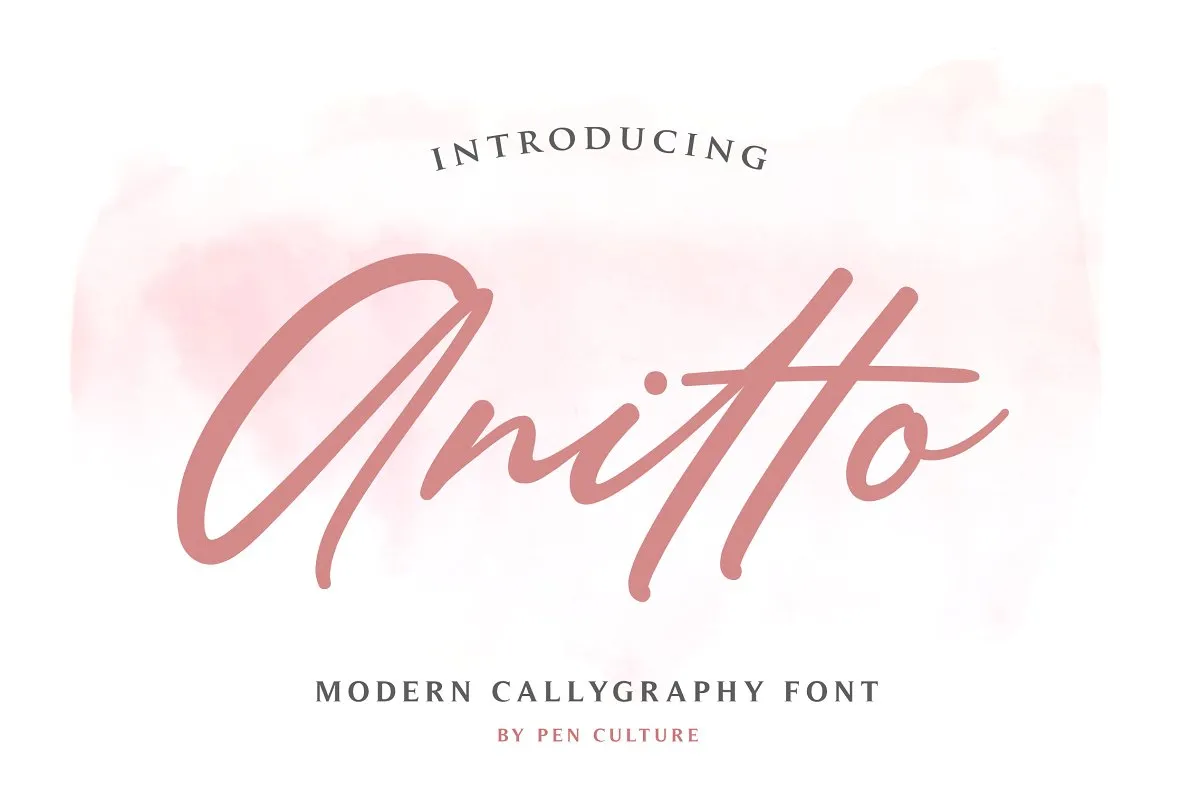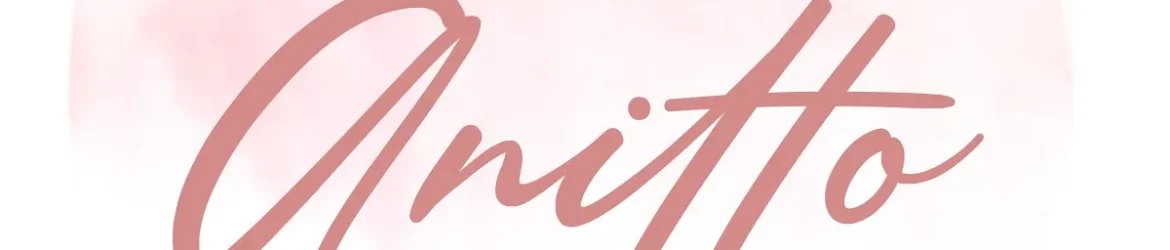
Anitto Calligraphy Font – Download Grátis
A Anitto Calligraphy Font é uma nova opção para designers que buscam expressar texturas delicadas e curvas suaves. Inspirada no encanto das manhãs dominicais nas pequenas vila do Brasil, esta fonte apresenta linhas leves e perfeitas para diversos usos. Com seu design cuidadoso por Pen Culture, a Anitto Calligraphy Font é ideal tanto para aplicativos em grandes tamanhos quanto para uso em mídias digitais menores. Sua natureza fluida e delicada tornam-a uma opção perfeita para criar texturas e estilos script elegantes em qualquer projeto. Combinar esta fonte com elementos gráficos que remetem ao cotidiano das pequenas cidades do Brasil pode resultar em trabalhos realmente memoráveis, destacando sua personalidade única e seus contornos delicados em cada caractere. Seja para nomes de empresas, designs de revistas ou até mesmo letras de música, a Anitto Calligraphy Font é uma escolha versátil que certamente se encaixará perfeitamente no seu próximo projeto.